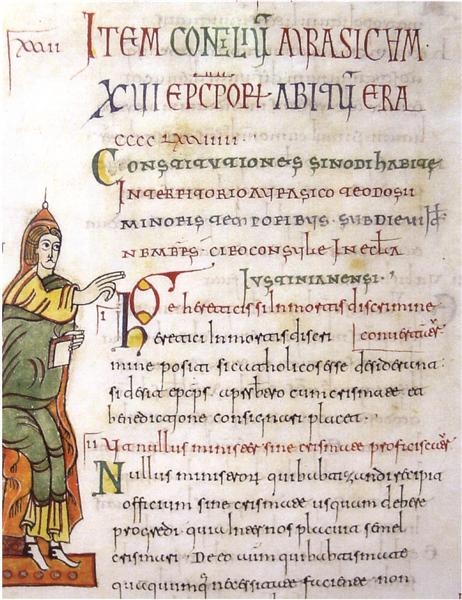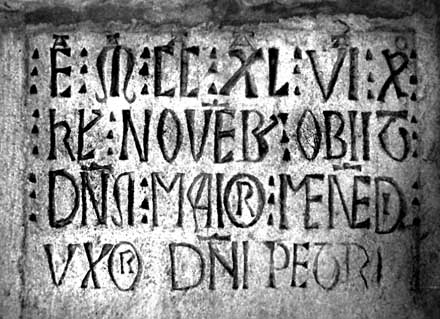
A letra visigótica
A letra visigótica foi escrita na Península Ibérica cristã a partir do século IV; foi o resultado da evolução local da letra romana. A Visigótica continuou em uso durante o domínio suevo e visigodo, e ficou na Península Ibérica até aos séculos XII-XIII. A Visigótica usou-se cursiva e redonda. A variante cursiva foi preferida para os documentos; a redonda, que integrou elementos do semi-uncial (um modelo de letra romano tardio), aparece sobretudo nos códices (livros manuscritos). Os principais centros de difusão foram Toledo, o Mosteiro de Santo Domingo de Silos, Leão, e outros. No emergente reino de Portugal, os scriptoria das sés de Braga e de Coimbra foram no século XI os principais centros onde a Visigótica se escreveu, uso que se prolongou durante o século XII e também alastrou a outros centros, como o Mosteiro de Santa Cruz de Coimbra.
A Visigótica atingiu a sua forma mais perfeita como caligrafia para livros. O declínio começou no século XI, por razões de intolerância religiosa. O Sínodo de Leão, realizado no final desse século, teria proibido a Visigótica na escrita de livros litúrgicos, como meio de supressão do rito moçárabe, nessa altura a ser substituído pelo rito romano da Reforma Gregoriana.
Ocódice Vigilano o AlbeldenseObra capital del escritorio albeldense y de la miniatura riojana es este códice, llamado Vigilano por el nombre de su principal autor Vigila 47. Contiene las actas de los concilios nacionales, de muchos generales y particulares de otras naciones, decretales pontificias, el Fuero Juzgo, el calendario mozárabe, tratados de cronología y aritmética... Era ésta una empresa realmente ardua cuya dificultad no escapaba al propio Vigila quien al comienzo del libro nos confía sus vacilaciones y temores al considerar la envergadura de la tarea que se le confiaba, y que al final emprende en nombre de Cristo y lleva hasta el fin. En las páginas finales del códice se hace mención en verso y se retratan Vigila acompañado de sus principales colaboradores, Sarracino a quien llama compañero (socius) y García, discípulo (discipulus), así como los reyes de Pamplona en cuyo tiempo fue redactada la obra, constando igualmente el nombre del monasterio en el que se realizó San Martín de Albelda y la fecha en que se terminó: 976. La ilustración de este códice es de extraordinaria riqueza, equiparable únicamente entre los de su época, a la de la serie de los Beatos, tanto por el número de folios miniados, algunos a página entera, como por la calidad de las miniaturas. Sin embargo los autores que han tratado de la miniatura española altomedieval, quizá deslumbrados por la originalidad de aquéllos, se han limitado a citarlo, señalando su lugar de origen, fecha en que se terminó, artistas que intervinieron en su ejecución, y añaden todo lo más una breve relación de las miniaturas más importantes describiendo someramente su estilo 51. Además mientras los primeros cuentan con varios estudios monográficos de conjunto y sobre alguno de ellos en particular, no existe, en cambio, ninguna monografía sobre este códice.